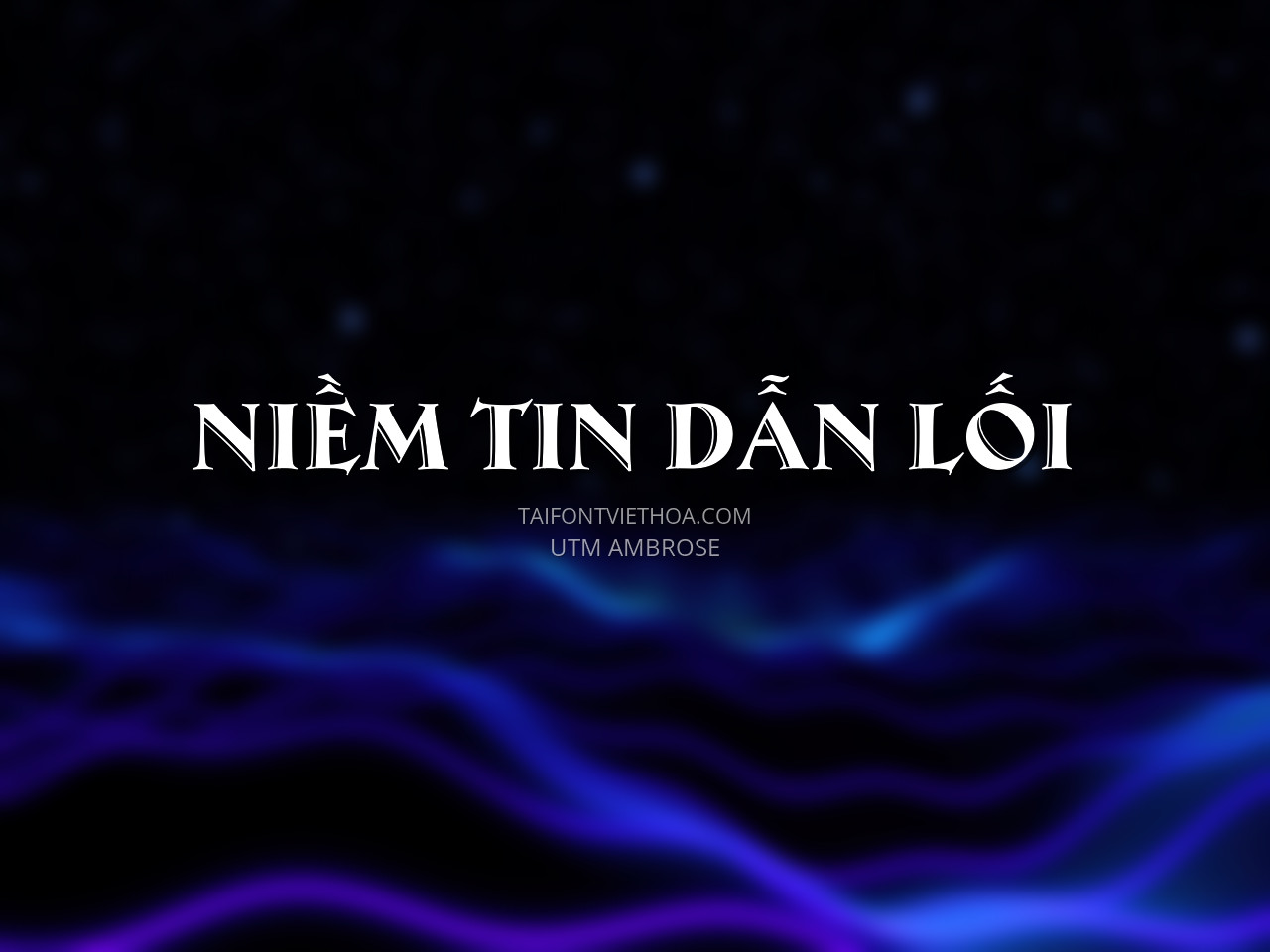
Font việt hóa UTM Ambrose
Giới thiệu về font UTM Ambrose
UTM Ambrose là phiên bản Việt hóa của font Ambrose – một kiểu chữ serif thanh lịch và truyền thống, được thiết kế bởi nhà thiết kế William Hill. Font gốc Ambrose nổi bật với các nét chữ có chân (serif) tinh tế, độ tương phản vừa phải và thiết kế hài hòa, tạo cảm giác trang nhã và dễ đọc. Phiên bản Việt hóa của font đã được hoàn thiện nhằm hỗ trợ đầy đủ tiếng Việt cùng hơn 200 ngôn ngữ khác, giúp mở rộng khả năng sử dụng cho các dự án đa dạng trên toàn cầu.
Đặc điểm thiết kế và ứng dụng của UTM Ambrose
UTM Ambrose có cấu trúc serif truyền thống với các đường nét mềm mại, phần chân chữ thanh thoát, cân đối và chi tiết. Font có độ tương phản nhẹ đến trung bình, phù hợp cho cả văn bản dài và tiêu đề nổi bật. Với các ligature tinh tế và ký tự thay thế, font mang đến sự linh hoạt trong thiết kế và cảm giác cổ điển sang trọng.
Font phù hợp với các ứng dụng như thiết kế sách, tạp chí, thiệp cưới, danh thiếp, bao bì sản phẩm cao cấp và các ấn phẩm quảng cáo đòi hỏi tính trang trọng. Các ngành nghề nên sử dụng gồm: xuất bản, thời trang, tổ chức sự kiện, nghệ thuật, giáo dục và thiết kế nội thất.